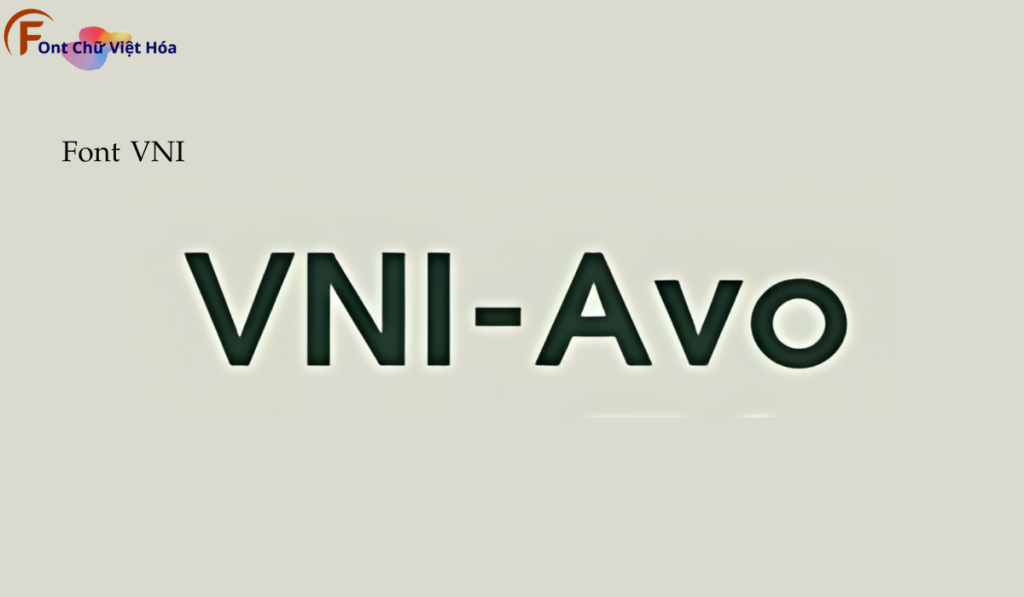
Font VNI Avo Việt Hóa
Phân loại: Cá tính, Độc đáo
Kiểu chữ: Có chân
Độ dày: Bold, Regular
Font VNI Avo Việt Hóa, thuộc bộ font VNI, mang phong cách hiện đại và sáng tạo, lý tưởng cho các dự án thiết kế như poster, logo, và bao bì sản phẩm. Với các nét chữ không chân và độ dày đều đặn, Font VNI Avo Việt Hóa không chỉ dễ đọc mà còn tạo cảm giác hiện đại và phá cách. Việc Việt hóa font giúp người dùng dễ dàng tích hợp vào các thiết kế tiếng Việt, mang lại sự tiện lợi và nâng cao tính thẩm mỹ.